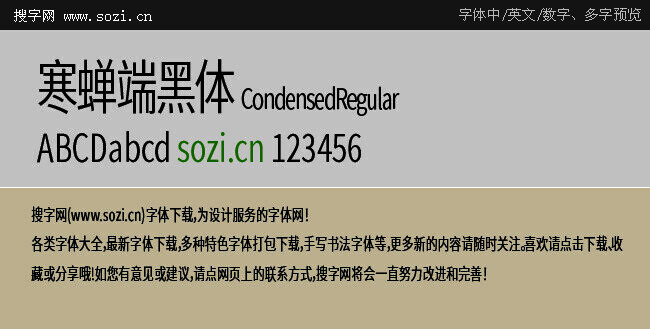
寒蟬端黑體CondensedRegular
搜字網(wǎng)給大家提供一款寒蟬端黑體CondensedRegular中文字體下載,寒蟬端黑體是基于思源黑體進(jìn)行調(diào)整的黑體字體,在原字體風(fēng)格上重新插值生成,Condensed系列的寒蟬端黑體是思源黑體的長(zhǎng)體版本。適用于標(biāo)題設(shè)計(jì)、海報(bào)設(shè)計(jì)、書(shū)籍排版以及網(wǎng)頁(yè)設(shè)計(jì)等應(yīng)用。